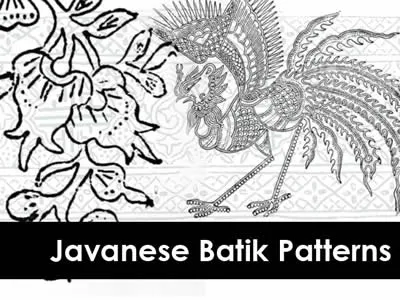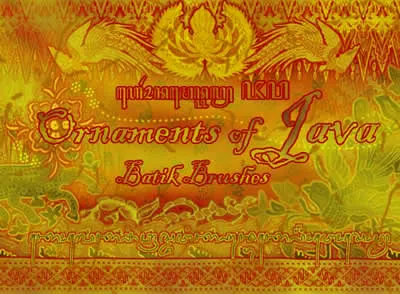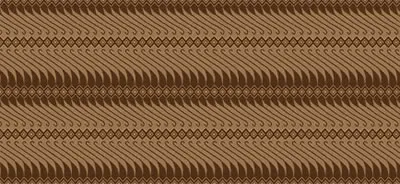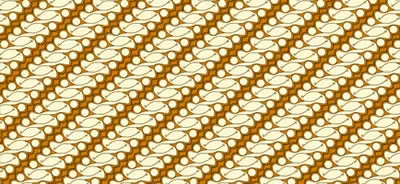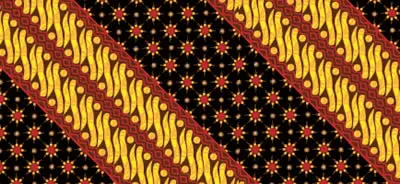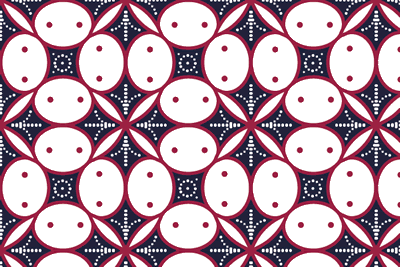
Artikel Computer 1001 kali ini menyajikan kumpulan sumber untuk font, brush, dan pattern Photoshop dengan tema batik.
Font Batik
- Indonesian Arts Culture – Font dingbat tokoh-tokoh wayang dan corak batik.
- Batik Dayak Font
- Batik Font 1
- Wayang Obama – Font corak batik serta dingbat gambar Presiden Obama dan tokoh-tokoh wayang.
- Eenvoudige Batik
Brush Photoshop Batik
Pattern Batik
- Batik 01 (Solo Batik)
- Batik 02 (Parang Rusak)
- Batik 03 (Famous Batik)
- Free Vector Indonesian Batik Pattern 04